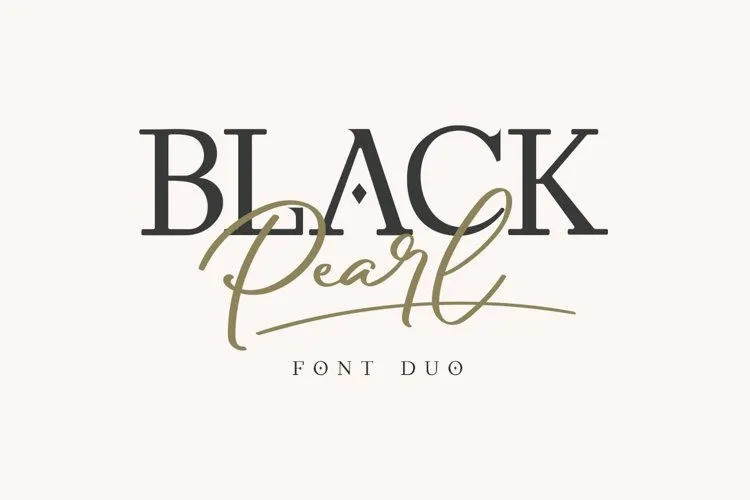
Black Pearl Font Duo – Download Grátis
A “Black Pearl Font Duo” é uma escolha perfeita para quem busca dar um toque luxuoso a qualquer projeto visual. Essa elegante dupla de fontes inclui elementos modernos e sofisticados, combinando serif e estilo de firma. Ela é ideal para aqueles que procuram dar ao seu trabalho um ar de requinte e bom gosto. Com detalhes meticulosamente elaborados em cada letra e ligação perfeita, essa fonte mantém o equilíbrio entre modernidade e elegância. É perfeitamente adequada para projetos que precisam exibir uma sensação luxuosa, pois carrega consigo a essência desejada, combinando sofisticação com estilo único.